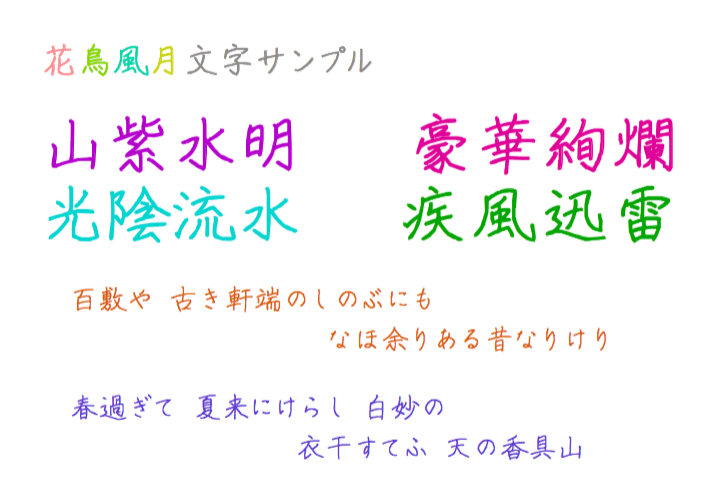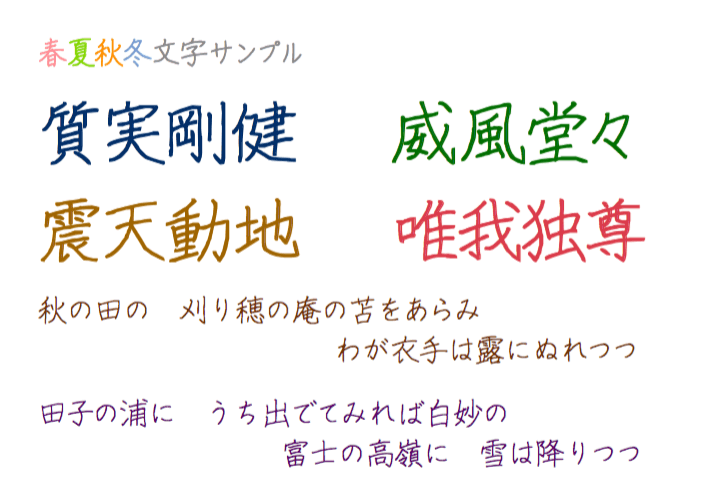
字が綺麗な人は羨ましい限りです。どうしてもうまくかけない人は、この記事で紹介している達筆なフォントをダウンロードし、利用してみてはいかがでしょうか?手紙をパソコンで仕上げたい方に最適なフォントとなっております。
851手書き雑フォント
「雑」がウリな手書きフォント。現在の収録文字数は32,433文字(スペース除く)、現在も増加中。
g_達筆(笑)
うまいっぽいけどうまいのかへたなのかよくわからない味のあるフォント。年賀状や、コミックの描き文字等にピッタリ。
あやのフォント
細めの和風フォント。期間限定で無料ダウンロード可能。商用利用の場合は有料版の購入が必要。
おみやげ-AL, KT, HR
素敵な手書き風フォント。字間を広くとってデザインすると雰囲気のある落ち着いた文字組になるとのこと。
花鳥風月
全体的にのびのびと優しい雰囲気のフォント。優しい雰囲気を演出するのにピッタリ。
春夏秋冬
細目の水性ボールペンで書いた字をイメージして作られ、一画一画丁寧に書かれた手書き風の楷書フォント。